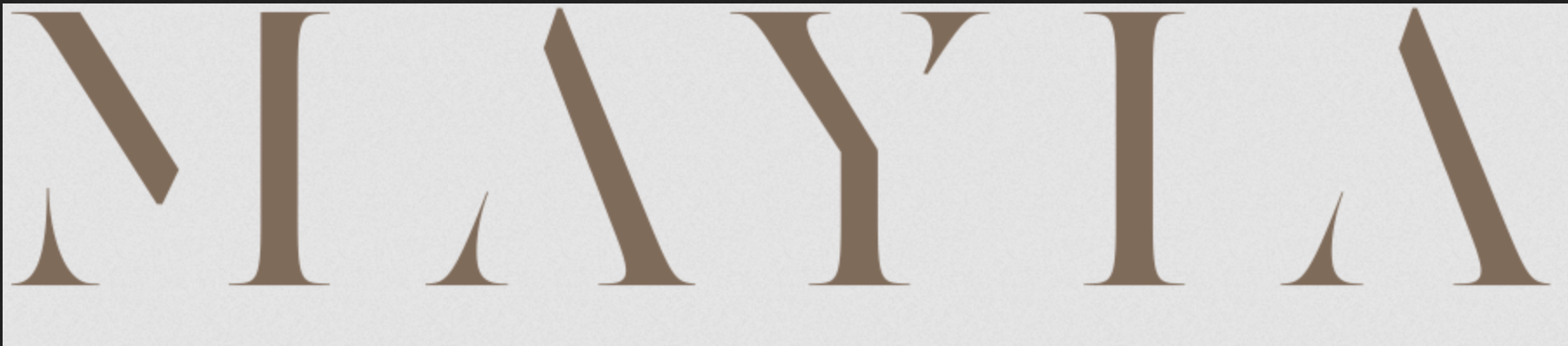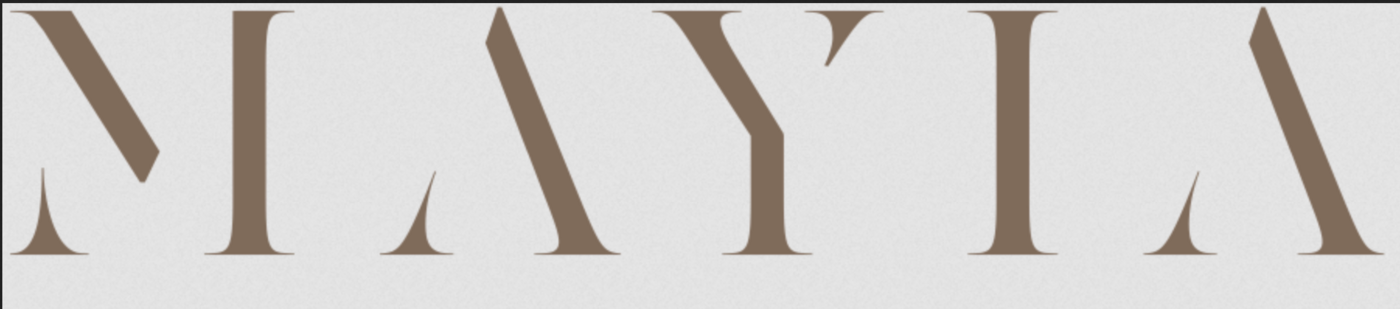
Modifizierter Font eines griechischen Hotels
bitte um Hilfe bei der Identifikation dieses Hotel-Schriftzuges (MAYIA). Ich gehe davon aus, dass der Font heftig modifiziert wurde (die dünnen Linien wurden vermutlich entfernt und die dazugehörigen Serifen nach oben und unten verlängert).
Ich suche nun schon länger nach dem verwendeten Basisfont und bitte ggf. um Hilfe.
Die Schrift hatte ich schon gefunden, aber die Serifen sind spitz zulaufend, das sollte mehr "slab serif" sein und dort, wo der Haarstrich fehlt auch deutlich zu klein. Die Lesbarkeit ist dadurch recht begrenzt. Das hat der/die Kreative beim Hotellogo eigentlich recht gut gelöst, wie ich finde.
Wenns gar nicht anders geht, muss ich das sowieso neu basteln. Kundin wünscht sich für ihren Namen genau diesen Font.